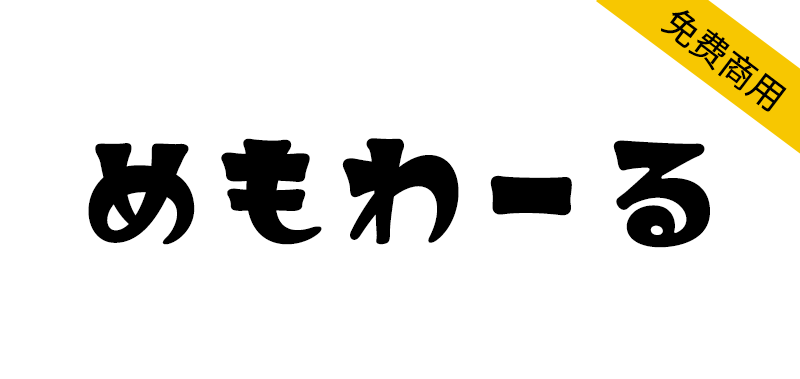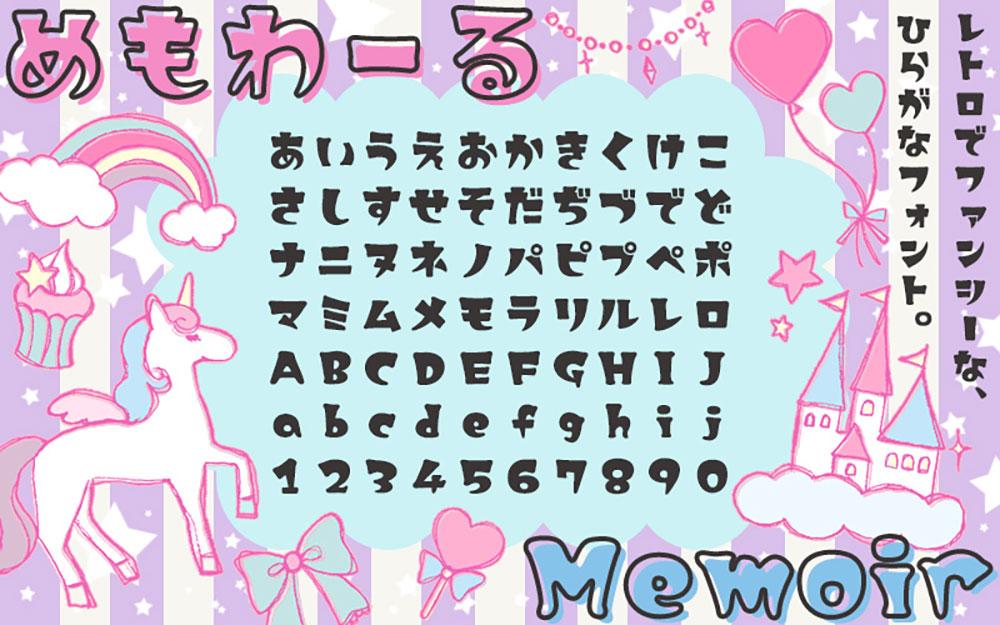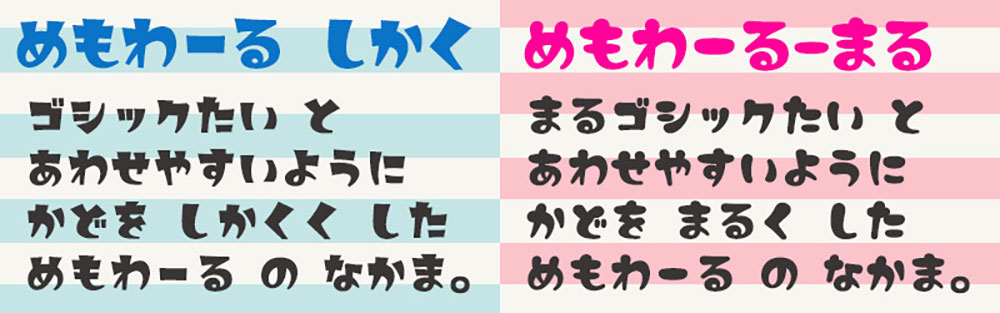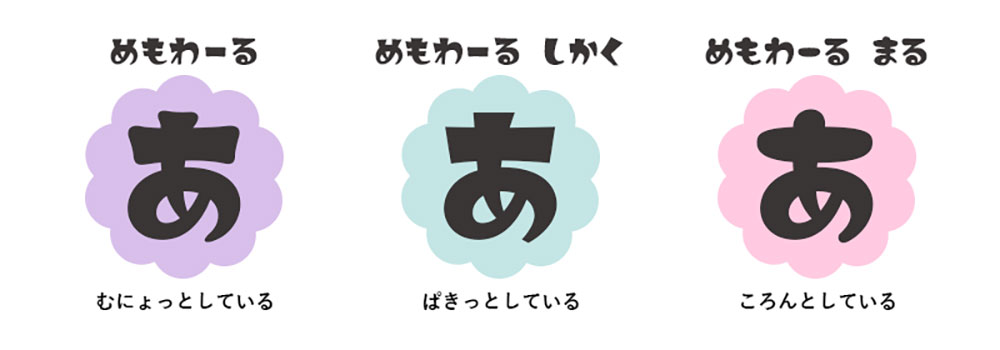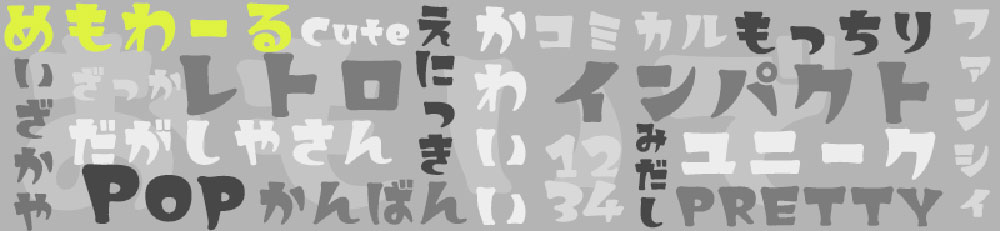
【めもわーる】一款精美时尚的复古流行风格日文字体
めもわーる(Memoir)这是一种以精美杂货为形象而创作的具有影响力的复古流行平假名字体。
但它似乎也适合像“hoppy”这样的词。
Memoir是一个法语单词,意思是记忆。
平假名、片假名、字母数字字符。
此外,还包括一些基本的标点符号(标点符号、括号等符号)。
ファンシー雑貨のイメージで作った、インパクトのあるレトロポップなひらがなフォントです。
でも「ホッピー」とかの単語にも似合いそう。
Memoir(メモワール)はフランス語で記憶や思い出のこと。
ひらがな・カタカナ・英数字。
おまけでいくつか基本的な約物(句読点や括弧などの記号)も入っています。